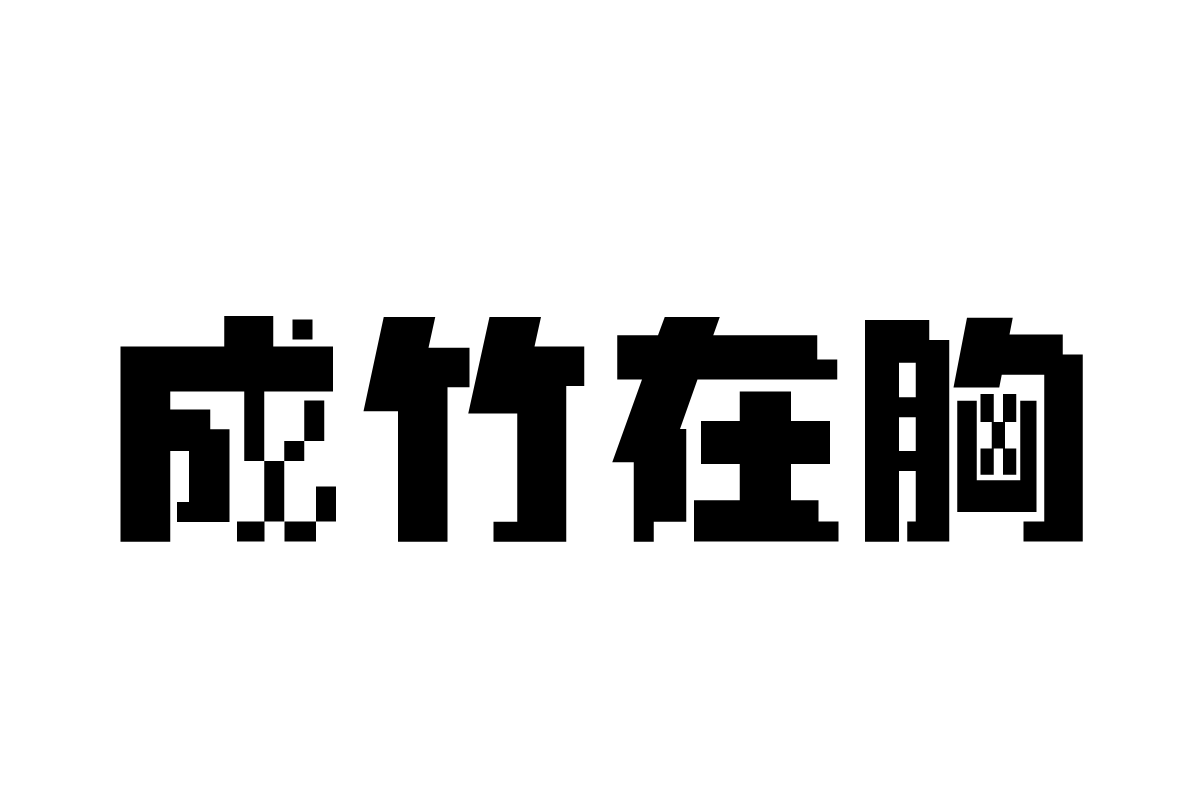
汉仪像素是一款非常受欢迎的字体,它以其独特的设计和风格深受广大用户的喜爱。这款字体采用了像素化的设计手法,将文字分割成一个个独立的像素点,使得字体看起来更加独特和有趣。同时,汉仪像素也具有很高的可读性和易用性,无论是在网页设计、海报制作还是其他任何需要文字的地方,都可以轻松使用。
此外,汉仪像素还具有很高的辨识度,无论是在黑白还是彩色的环境下,都能保持其独特的风格。同时,它的字体大小、颜色等参数也可以根据需要进行自由调整,满足不同场景的需求。
总的来说,汉仪像素是一款功能强大、易于使用的字体,无论是专业人士还是业余爱好者,都可以从中找到乐趣和灵感。